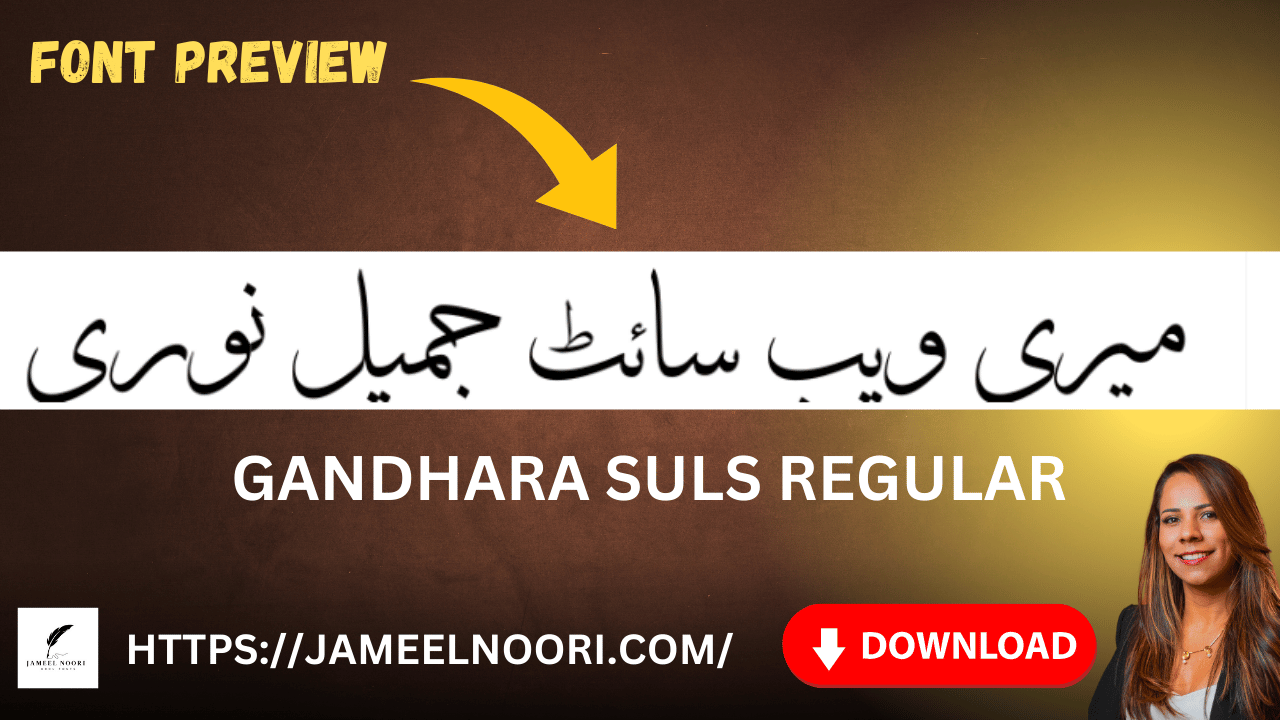
Gandhara Suls Regular Download Urdu Font ek bohot hi popular aur stylish Urdu typeface hai jo Arabic-style calligraphy aur Urdu typography lovers ke liye perfect choice hai. Ye font un users ke liye best hai jo InPage, MS Word, Photoshop aur designing software me elegant Urdu likhna chahte hain.
๐งฉ What is Gandhara Suls Regular Download Urdu Font?
Gandhara Suls Regular Urdu Font aik Regular TrueType Font (TTF) format me available Urdu typeface hai. Ye font Arabic aur Persian calligraphy ka modern combination hai jo Urdu likhne walon ko ek elegant aur readable style deta hai.
Iska design โSulsโ style par base karta hai โ jo traditionally Arabic scripts me use hota tha. Ab ye digital form me Urdu users ke liye available hai, jise aap free me download kar sakte hain.
Key Features of Gandhara Suls Regular Urdu Font
Niche diye gaye Urdu Font ke kuch important features uski popularity ka saboot hain:
| Design Style | Arabic-Persian inspired calligraphy |
Ye font simple Urdu likhne ke alawa professional design projects ke liye bhi ideal hai.
๐ก Gandhara Suls Regular Font ke Major Benefits
Agar aap Urdu design ya writing ke field me kaam karte hain, to Urdu Font aapke liye bohot useful sabit hoga.
Major Benefits:
- Professional Look: Stylish aur elegant Urdu script.
- Perfect for Branding: Ideal for logos, posters, aur book titles.
Ye sab features is font ko Pakistan me Urdu writers, designers, aur publishers ke liye favorite banate hain.
๐จ Where Can Gandhara Suls Regular Font Be Used?
Urdu Font har jagah use ho sakta hai jahan Urdu ka elegant touch chahiye ho.
Popular Use Cases:
- Urdu Poetry designing
- Book covers aur titles
- Newspaper headings
- Islamic calligraphy designs
- YouTube thumbnails
- Urdu website headings
Iska modern aur stylish design Pakistan ke creative designers ke liye ek perfect choice hai.
Is font ki Arabic-Persian inspired styling isey Islamic aur educational projects ke liye bhi suitable banati hai. Har Urdu lover is font ko apni system library me rakhta hai โ ek must-have font!
Gandhara Suls Regular Download Urdu Font Urdu aur Arabic calligraphy lovers ke liye ek ultimate, free aur elegant font hai. Iska clean structure, easy installation aur compatibility ise Pakistan ke top Urdu fonts me shamil karta hai. Agar aap Urdu typing ya designing projects me ek unique aur readable font chahte hain to Gandhara Suls Regular aapke liye perfect choice hai.